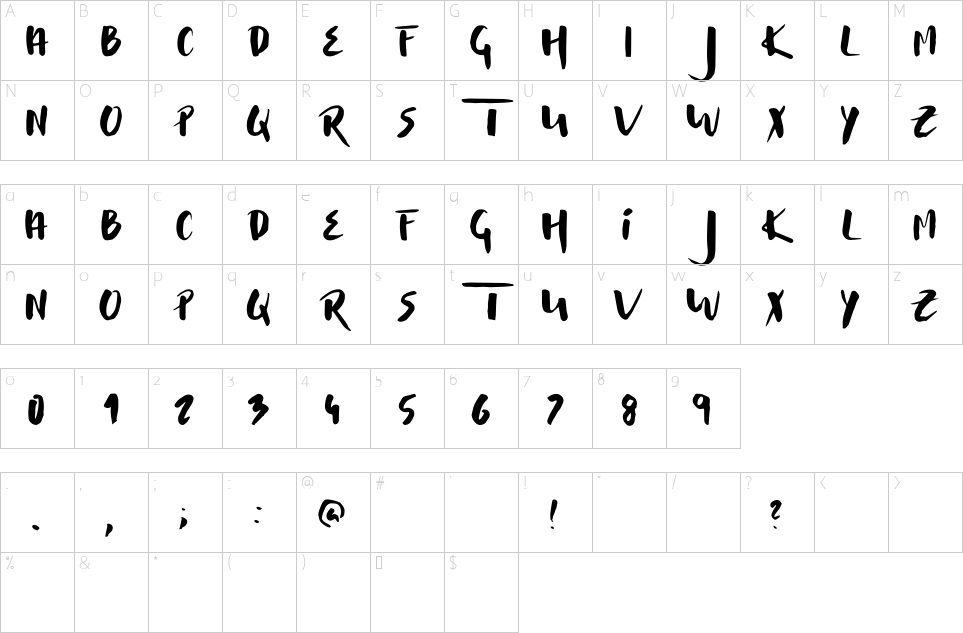
A Musterion font é um adorável desafio para todos os apaixonados por letras e digitais. Desenvolvida por Leosupply.co, esta fonte é perfeita para um amplo espectro de projetos digitais, desde textos responsivos para sites até pequenas gráficas pessoais. Com um design elegante e detalhado, a Musterion não apenas oferece uma aparência atraente, mas também garante uma legibilidade excepcional em qualquer dispositivo. Com 6,604 downloads, é evidente que esta fonte está ganhando popularidade rapidamente entre os criadores de conteúdo digital. Se você está em busca de uma fonte agradável e de fácil manuseio para seus projetos futuros, a Musterion font é uma ótima escolha.